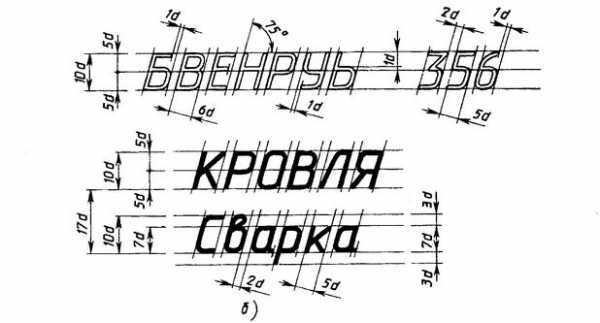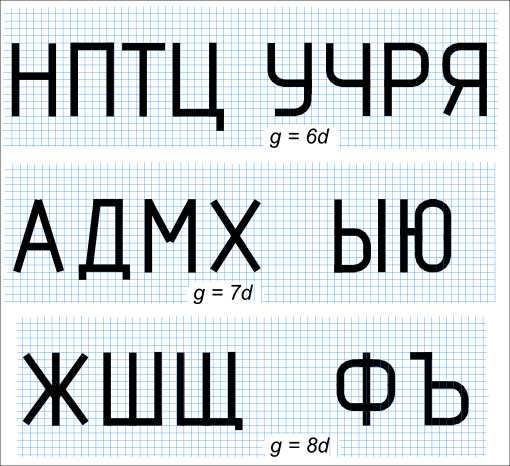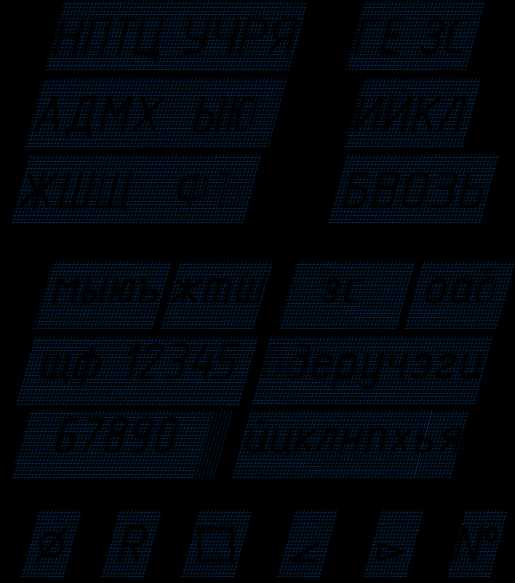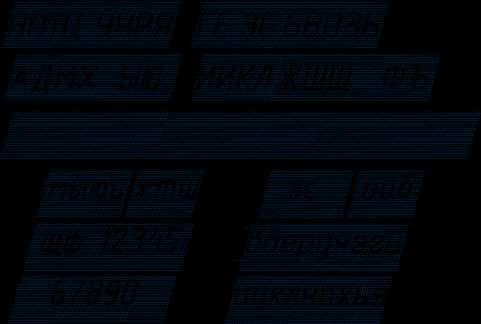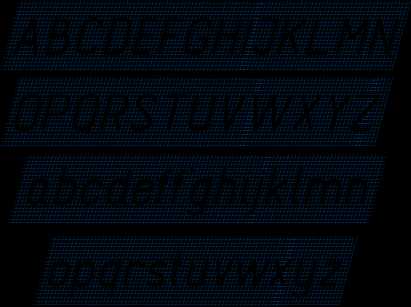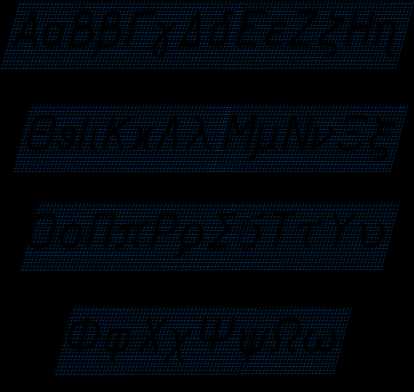
Чертежные шрифты (ГОСТ 2.3304-81) применяются для выполнения пояснительных надписей на чертежах. ГОСТ устанавливает следующие типы шрифтов (см табл.): — тип А(d = h 1/14) без наклона и с наклоном около 75°; — тип Б(d = h 1/10) без наклона и с наклоном около 75°. HTML код таблицы, примеры
Размер шрифта h — высота прописных (заглавных) букв и цифр измеряемая в миллиметрах. Стандарт устанавливает следующие размеры шрифта: 1,8; 2,5; 3,5; 5; 7; 10; 14; 20; 28; 40. Высота строчных букв определяется по соотношению c = (7/10)h или если шрифт дан An то его высота строчных букв может быть взята по размеру шрифта An-1. Например размер шрифта взятый вами для какой либо надписи 40. Это значит h = 40 и тогда c = (7/10)h = 28. Толщина линий d определяется в зависимости от типа и высоты шрифта, например: — Для шрифта типа A(узкого) d = (1/14)h; — Для шрифта типа Б(широкого) d = (1/10)h. Ширина буквы определяется: — в зависимости от высоты шрифта ![]() Чертежные шрифты Построение прописных букв русского алфавита без наклона ![]() Чертежные шрифты Построение прописных букв русского алфавита без наклона по временной вспомогательной сетке с размером ячейки равным толщине линии. Когда величина букв небольшая, размер ячейки определяется ее шириной и высотой. ![]() Чертежные шрифты Построение строчных букв русского алфавита без наклона ![]() Чертежные шрифты Построение строчных букв русского алфавита и цифрового ряда без наклона ![]() Чертежные шрифты тип Б(d = h 1/10) с наклоном около 75° выполненные в масштабе М1:1 №10, №7 и №5: ![]() Чертежные шрифты ![]() Чертежные шрифты Латинский алфавит ![]() Чертежные шрифты Греческий алфавит ![]() Чертежные шрифты Для быстрого и качественного выполнения надписей на чертеже может быть применена специальная линейка, Чертежные шрифты которую несложно изготовить из тонкого твердого картона, вырезав в нем три окна. Левое окно предназначено для написания в нем прописных букв и строчных букв, имеющих верхнее окончание. В среднем окне пишутся обычные строчные буквы. В правом окне пишутся строчные буквы, имеющие нижнее окончание. В случае использования данной линейки необходима минимальная разметка — это линии строк. В качестве примера графической работы с преобладанием темы Чертежные шрифты смотри: Титульный лист + |
Цифры стандартными шрифтами
В подборе шрифтов для текста написано не мало статей, а вот в выборе цифр явная дискриминация. Посмотрите как выглядят цифры, начертанные шрифтами из стандартного набора популярных операционных систем.
Все цифры чуть ниже подписаны используемыми шрифтами.
Выше показаны цифры различными шрифтами — стандартными и популярными. Помимо шрифтов показаны шрифты по умолчанию из семейств шрифтов.
На чертежах и схемах кроме размерных чисел наносят различные надписи как в графах основной надписи (угловом штампе), так и на поле чертежа — надписи с обозначением изображений, а также надписи, относящиеся к отдельным элементам изображаемого изделия или здания. Надписи должны быть ясными и четкими.
Чертежные шрифты.
ГОСТ 2.304—81* устанавливает шрифты для надписей, наносимых на чертежах и технических документах всех отраслей промышленности и строительства. Чертежные шрифты характеризуются простотой конструкции букв, цифр и знаков. Для лучшего восприятия конструкции шрифта его построение показано на вспомогательной сетке (рис.1 а, б), шаг линий которой зависит от толщины линий шрифта. Наклон букв и цифр данного шрифта к основанию строки равен примерно 75°.
Рис.1. Чертежный шрифт с наклоном (тип Б): а — прописные буквы, б — строчные буквы, в — арабские цифры
Размер шрифта характеризуется высотой h прописных букв в миллиметрах (см таблицу).
Таблица Размеры букв и цифр чертежного шрифта типа Б по ГОСТ 2.304-81*